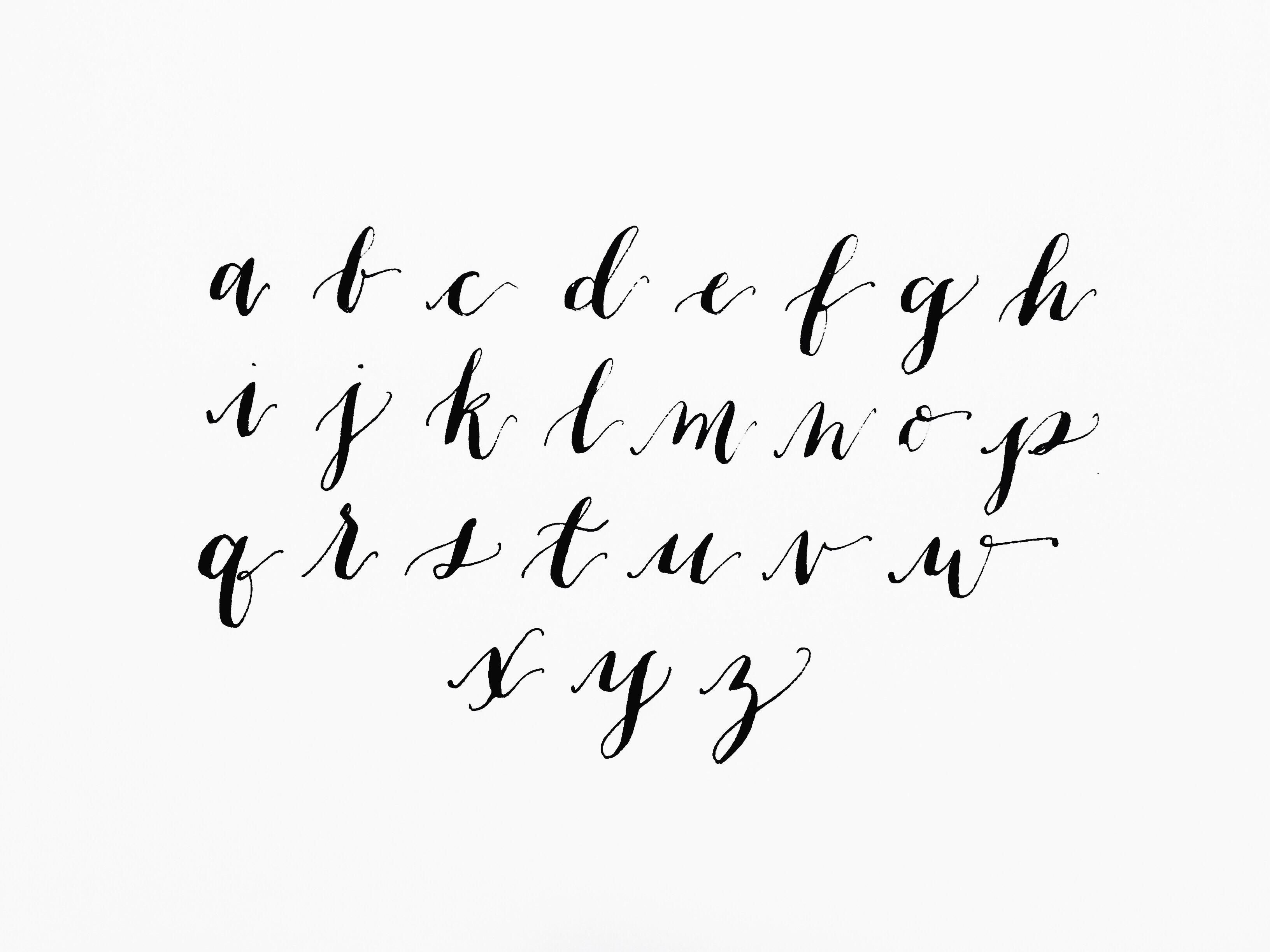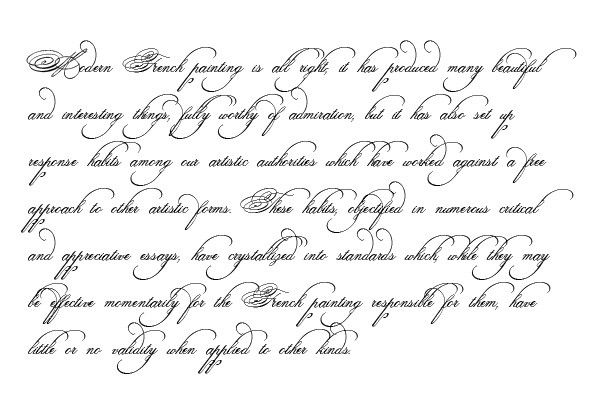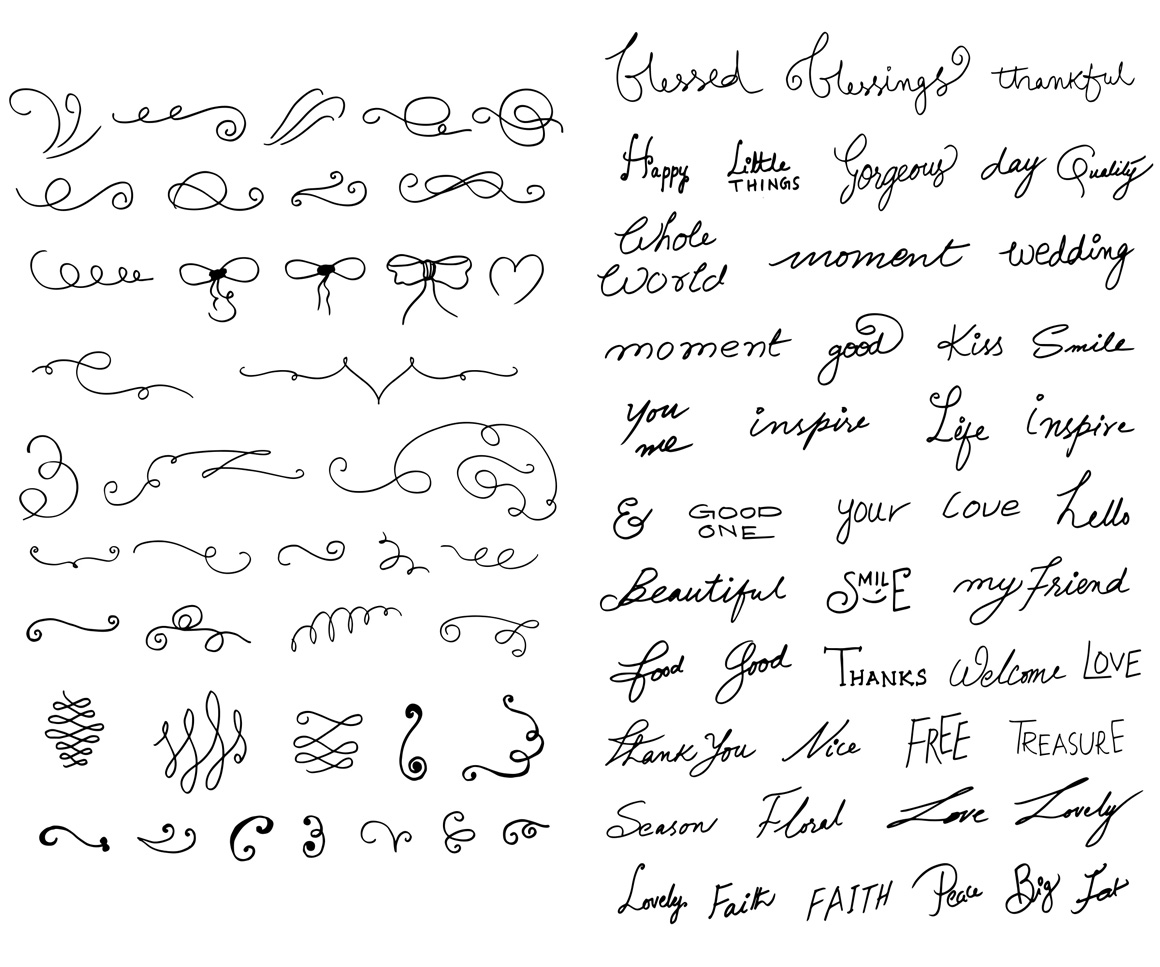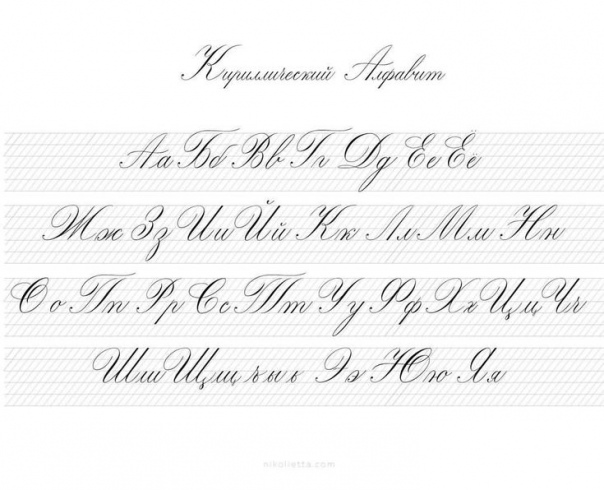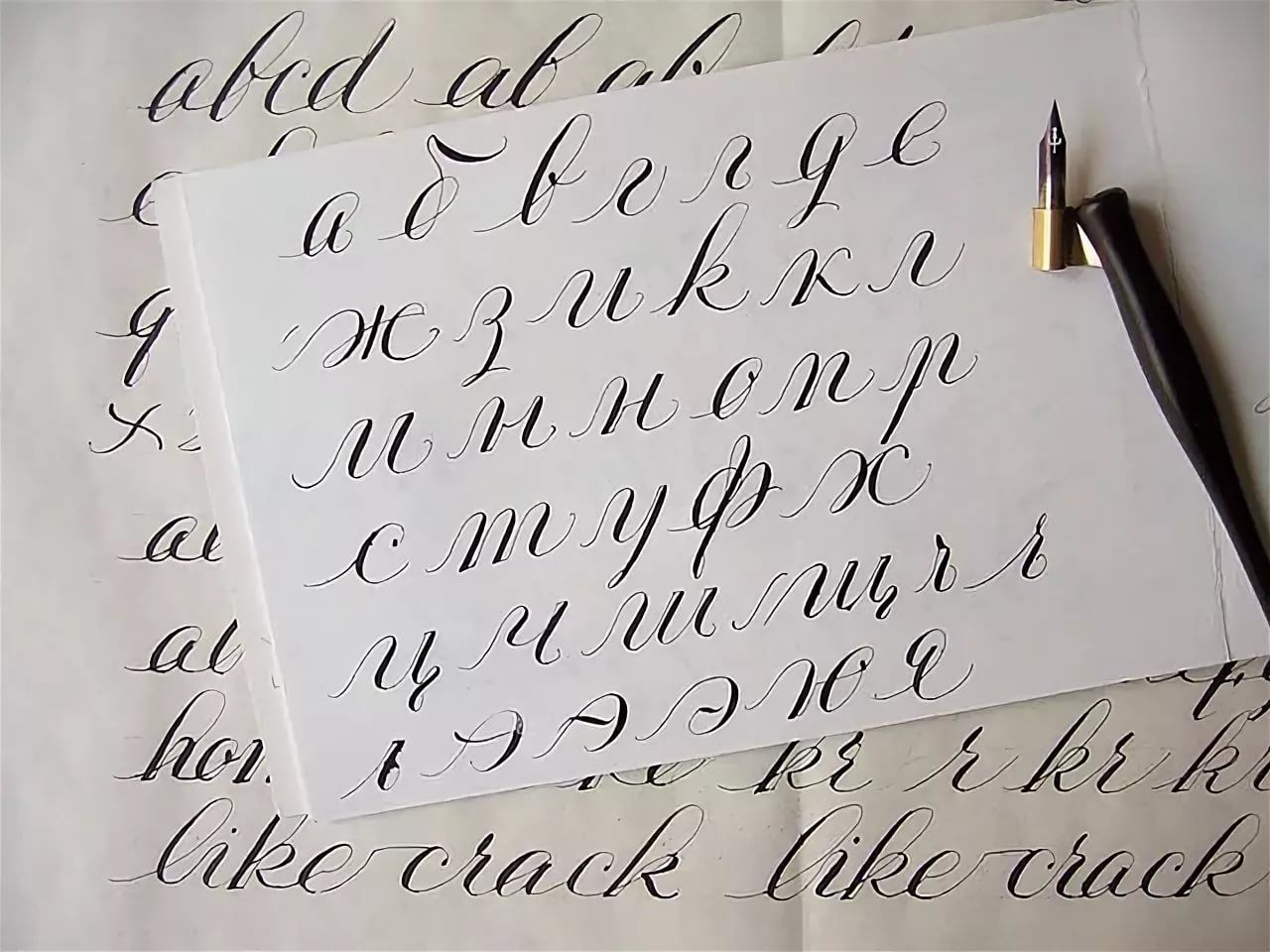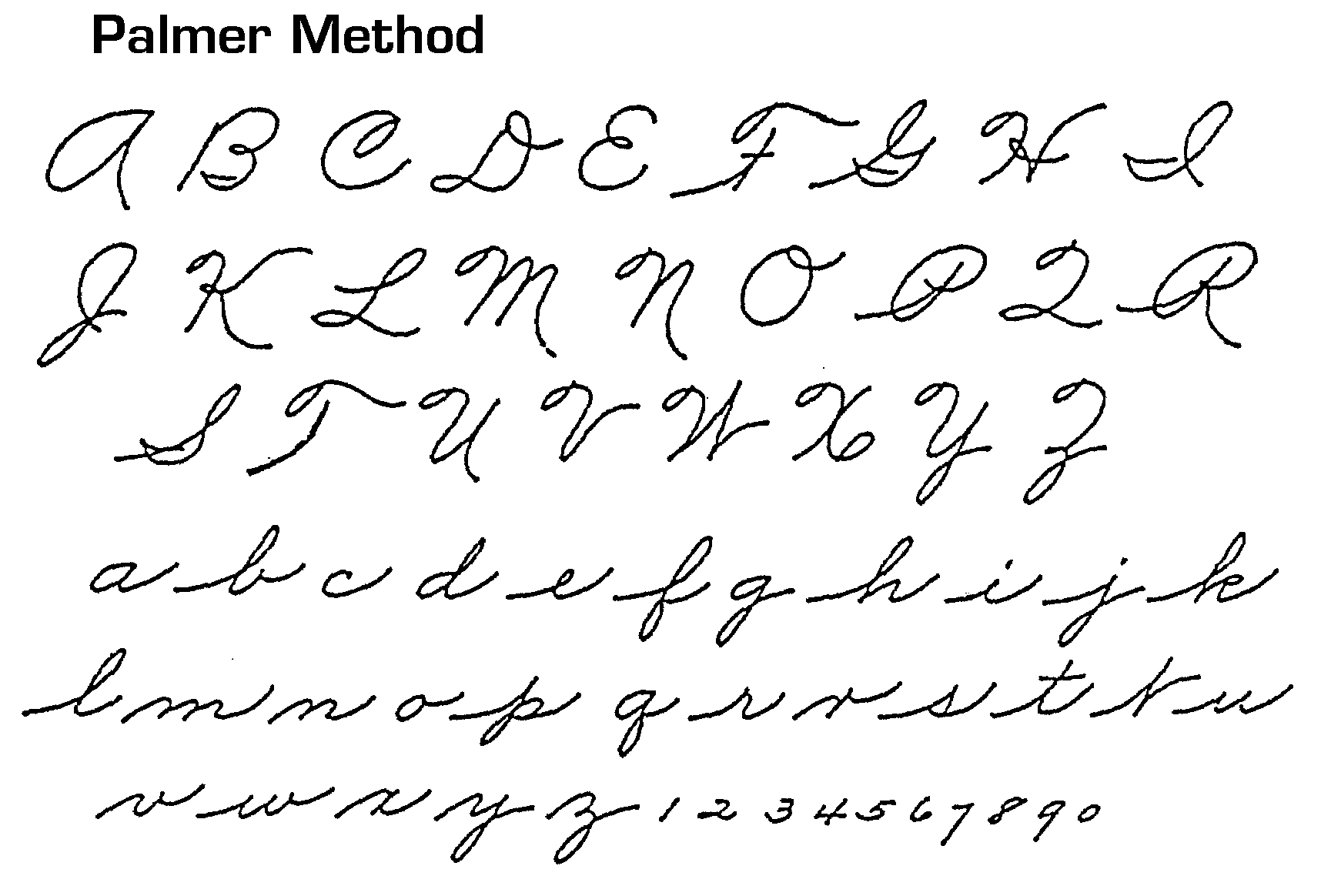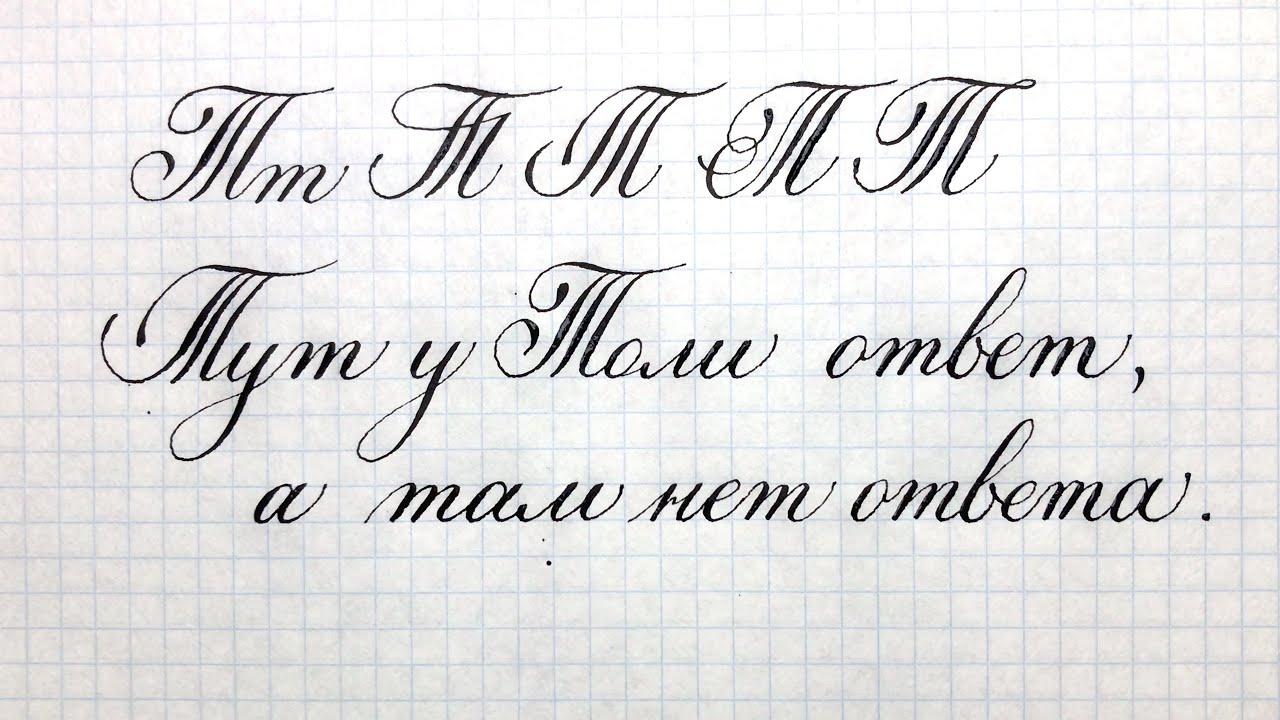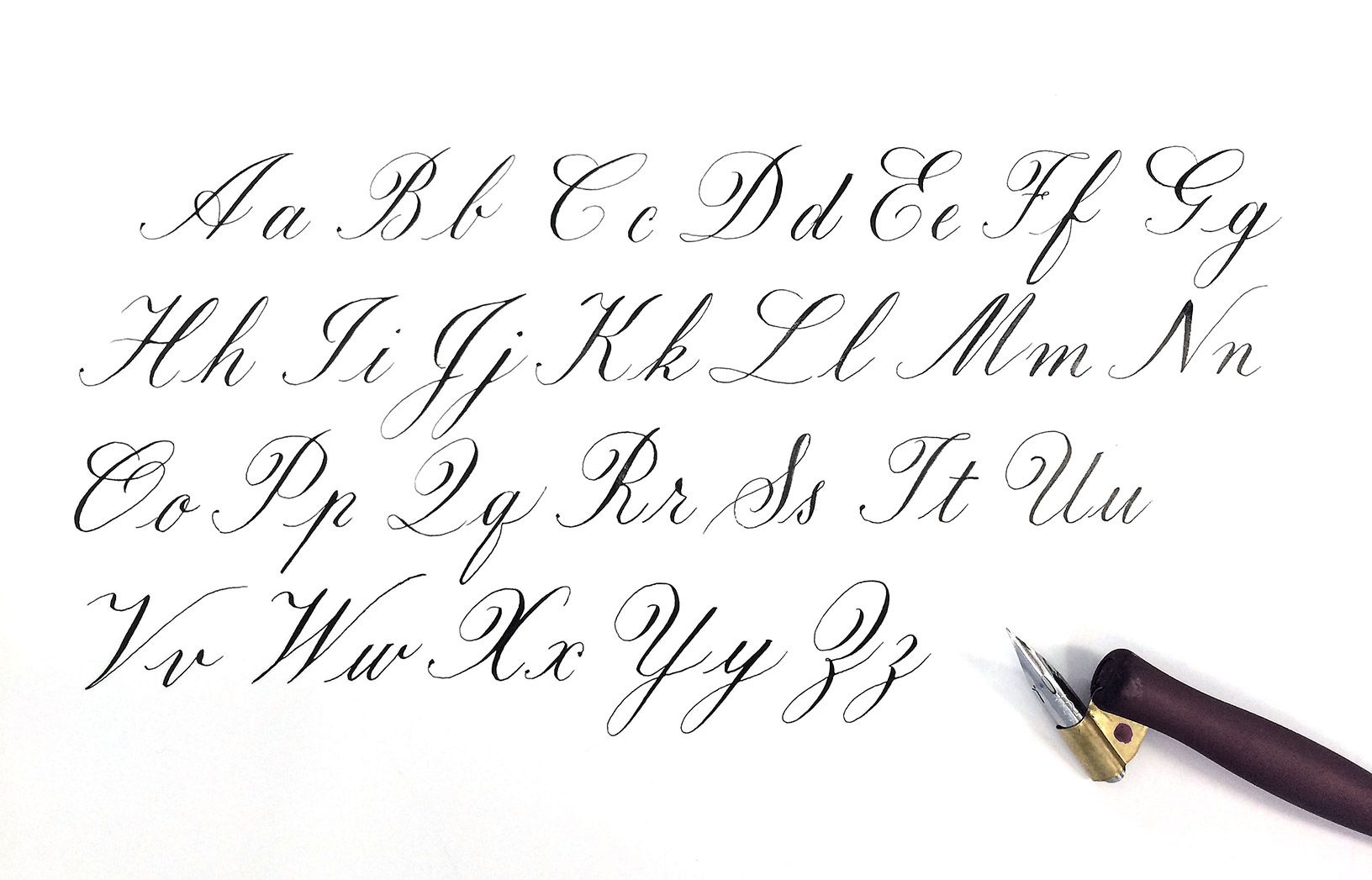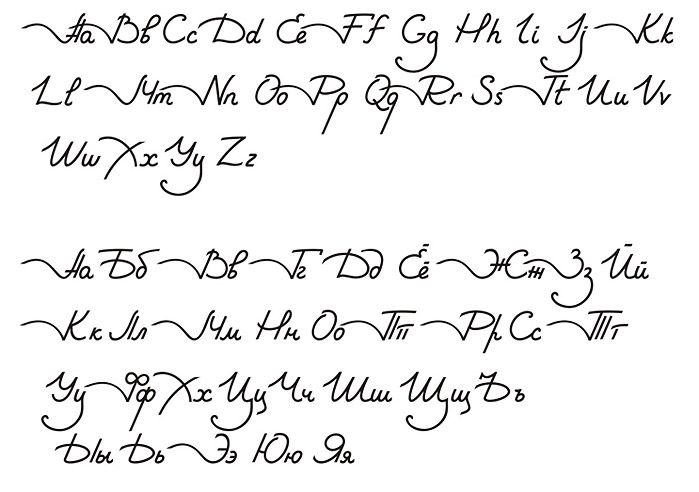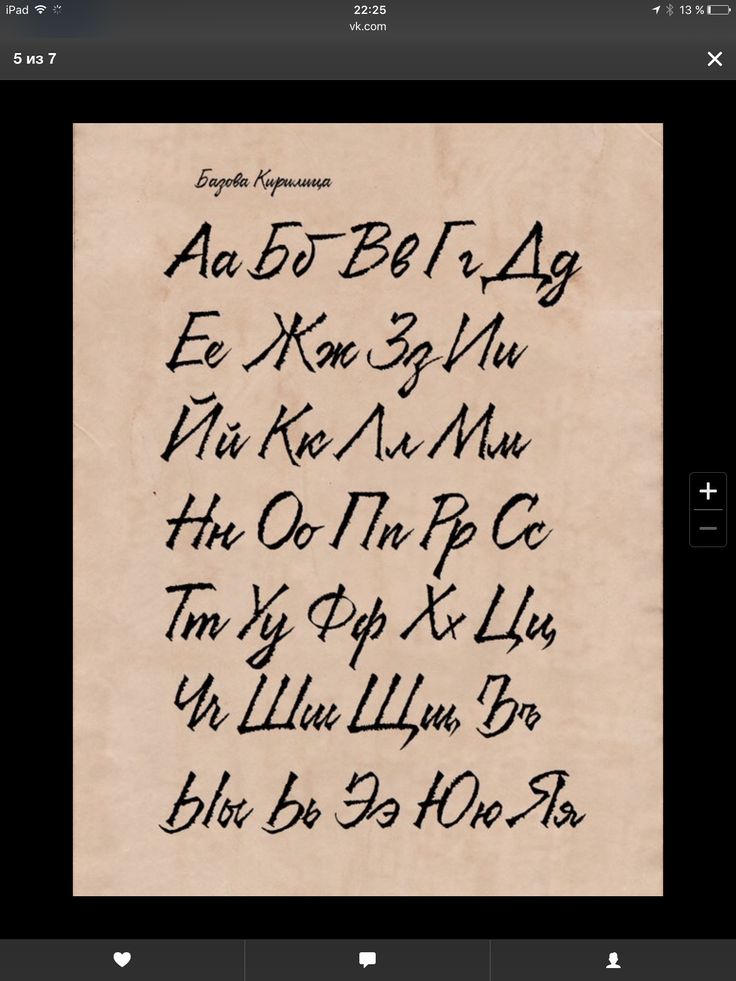
Роспись шрифт — 88 фото
Signature шрифт
Каллиграфический шрифт для подписи
Стиль леттеринг шрифты
Signature шрифт
Надписи в разных стилях
Шрифт копперплейт кириллица каллиграфия
Каллиграфическая подпись
Почерк спенсериан
Красивые шрифты для рисования
Каллиграфический шрифт
Надпись каллиграфическим почерком
Красивый шрифт автограф
Каллиграфические буквы английского алфавита
Шрифты для логотипа
Красивые буквы алфавита
Текстовые логотипы
Каллиграфические шрифты для начинающих
Красивые буквы для тату
Шрифты леттеринг ручкой
Логотипы с рукописным шрифтом
Красивый шрифт на английском
Шрифт для подписи
Красивый шрифт для конспектов
Красивый шрифт
Шрифты английские
Почерк спенсериан
Декоративный почерк
Каллиграфический почерк алфавит
Каллиграфия прописи
Флориши леттеринг каллиграфия
Тату эскизы для девушек надписи
Эскизы шрифтов
Творческие шрифты
Каллиграфия упражнения копперплейт
Надписи для скетчбука
Спенсериан каллиграфия
Красивые расписные буквы
Теги для новичков маркером
Крутые шрифты для татуировок
Русский алфавит спенсериан каллиграфия
Каллиграфические надписи
Тату эскизы шрифты
Тату эскизы надписи
Английская каллиграфия
Красивые буквы для тату
Декоративная каллиграфия
Каллиграфия брашпеном алфавит
Русский алфавит в стиле Леттеринга
Буквица каллиграфия Славянская каллиграфия
Каллиграфические надписи
Размашистый шрифт
Новый год красивым шрифтом
Шрифтовая композиция каллиграфия
Рукописный леттеринг
Буквы каллиграфическим почерком
Буквы красивым шрифтом
Стилизованные буквы
Надписи чёрной ручкой
Поздравительные надписи для скрапбукинга
Красивый шрифт на английском
Красивые прописные буквы
Шрифт Барокко
Советский леттеринг шрифт
Шрифты для подписи на русском
Beauty красивый шрифт
Шрифт рисунок
Шрифт в стиле Модерн
Красивый объемный шрифт
Стильный шрифт
Каллиграфический почерк алфавит
Буквы в разных стилях
Леттеринг алфавит английский
Каллиграфическое рисование пером
Каллиграфические буквы
Логотип инициалы
Каллиграфический шрифт
Шрифт роспись
Декоративный шрифт
Красивый рукописный шрифт
Инициалы на свадьбу
Буквы в разных стилях
Каллиграфия копперплейт алфавит
Кириллические шрифты для логотипов
Почерк спенсериан
Шрифты для тату
Граффити шрифты
ruВ прошлой статье мы говорили о том, как разные шрифты отличаются друг от друга по своему рисунку и как эти отличия отражаются на их характере и удобочитаемости. Сегодня затронем другие аспекты, связанные с буквами, которые могут влиять на выбор шрифта для бренда.
Каллиграфия, леттеринг, шрифт
Все, конечно, что-то слышали о каллиграфии. Наверняка ещё в детстве встречали словосочетание «каллиграфический почерк», что на бытовом уровне значило просто «красивый почерк».
Русское рукописное письмо или попросту школьные прописи.
На самом деле почерк и каллиграфия — немного разные вещи. Почерк — просто характерные для любого пишущего детали его рукописного письма.
Кроме каллиграфии есть ещё леттеринг. Если упрощать, то они отличаются между собой тем, что каллиграфия пишется за один подход, минимальными движениями инструмента, а формы знаков леттеринга могут тем или иным способом многократно правиться и вообще чаще скорее рисуются, чем пишутся.
Чем же тогда шрифт отличается от леттеринга? Дело в том, что набором знаков шрифта можно пользоваться бесконечно, в том числе набирая тексты на клавиатуре, и все повторяемые символы будут идентичны. В то время как леттеринг — штучная работа.
С помощью копирования знаков из леттеринга можно сделать шрифт, но тогда он и перестанет быть леттерингом. Любопытно, что при всём этом, как мы писали в первой части, многие из шрифтов в своей графике опираются на каллиграфическую основу написания букв.
В брендинге леттеринг часто применяется, если речь заходит о логотипах, где уникальные буквы иногда помогают создать особенный образ.
В то же время, в логотипах с использованием шрифтов в качестве основы нет ничего плохого, если это решение соответствует задаче, а айдентика состоит не только из логотипа.
Что касается каллиграфии — из-за высокой вариативности результата она не так легко применима. Например, если речь идёт о пригласительных на свадьбу, то их число ограничено и позволяет оформлять их каллиграфией, переделывая заново то, что получилось не так хорошо. Но если это какой-то бренд с многотысячными тиражами, то каллиграфия может быть размножена только в виде цифровых копий, что уже позволяет усомниться в том, что это именно она. Однако даже в этом случае продукт может получить особую атмосферу рукотворности, и этим приёмом часто пользуются.